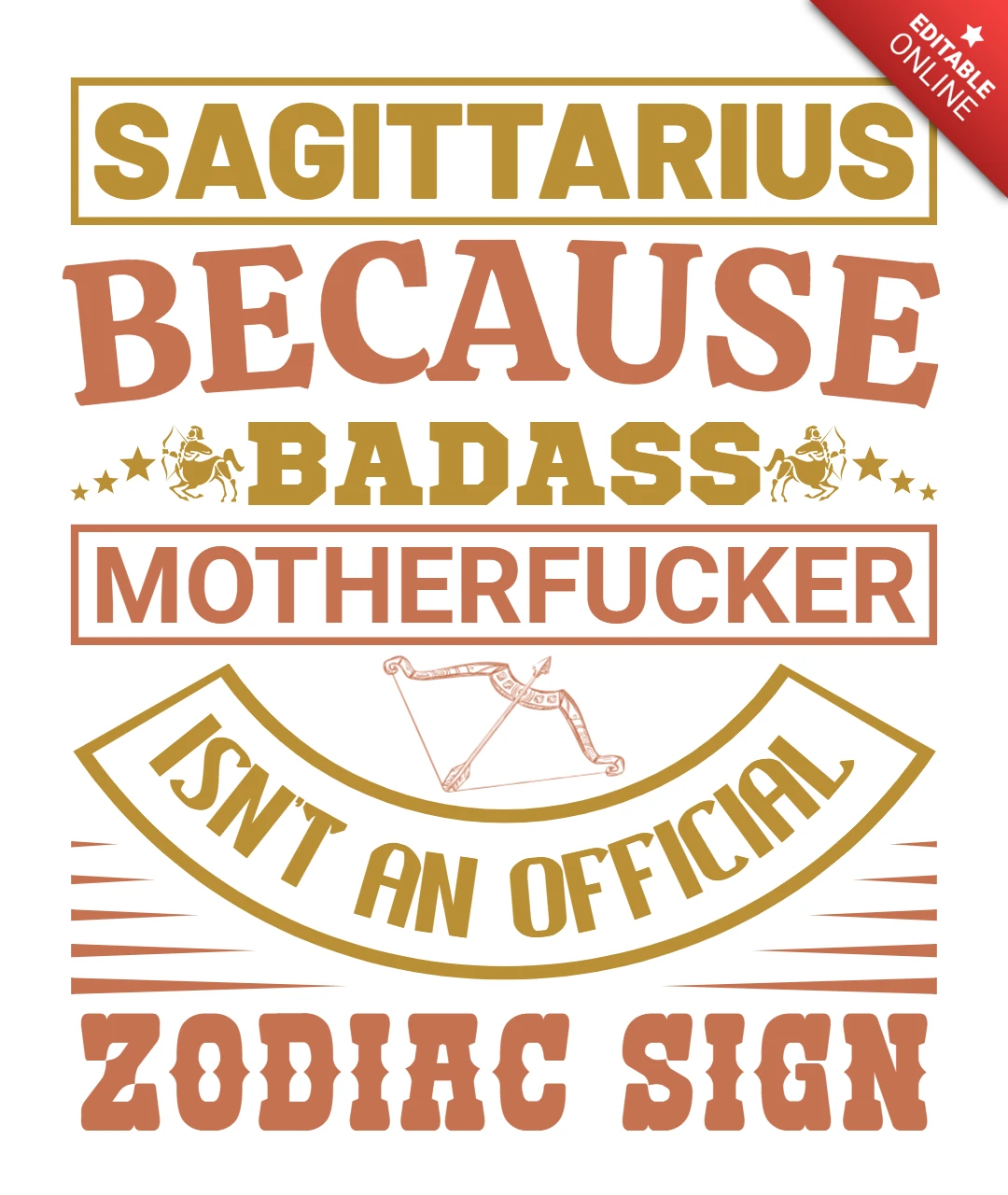
Dikke typografie ontwerpsjabloon voor het sterrenbeeld Boogschutter
Bewerken in Design Studio Downloaden in JPGVerhoog je kledingmerchandising met onze gedurfde boogschutter ontwerp sjabloon, met vintage typografie en humoristische illustraties die een statement maken voor elke zodiacliefhebber.